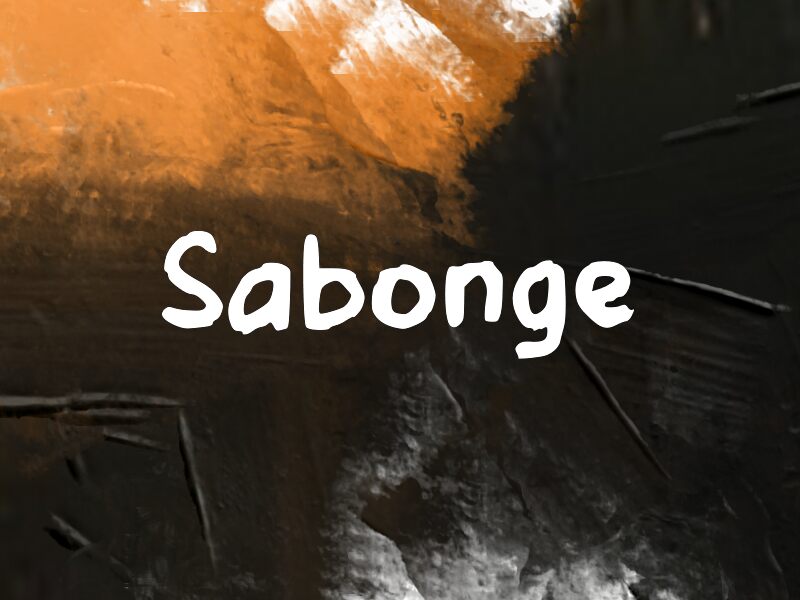
Sabonge
Sabonge, da Wep, é uma fonte estilo pincel gratuita caracterizada por traços arredondados e cheios, que dão a sensação de terem sido pintados em um único gesto descontraído. A suavidade ao longo das bordas e o ritmo compacto e desenhado à mão mantêm um ar casual e direto, em vez de polido ou caligráfico.
Essa textura confere aos títulos curtos um papel de destaque em menus de café, rótulos de produtos, cabeçalhos de cartazes, gráficos para redes sociais e embalagens informais. A Sabonge também é ideal para materiais de eventos infantis ou marcas artesanais, onde as formas amplas e o ritmo levemente irregular ajudam o texto a parecer pessoal e acessível.